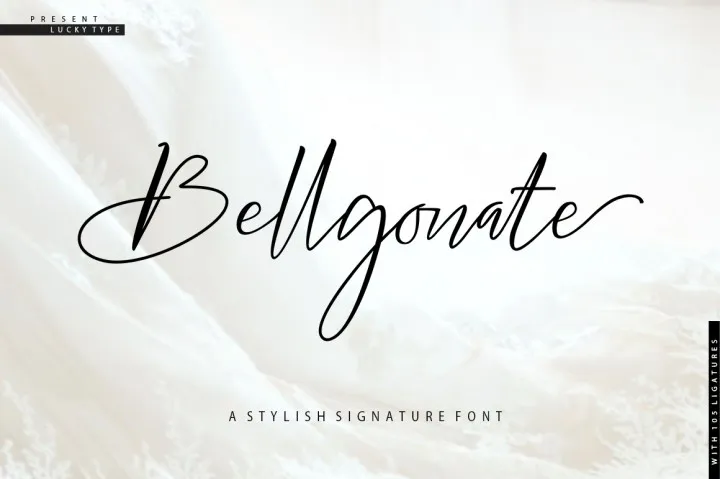
Bellgonate Signature Font – Download Grátis
A Bellgonate Signature Font é uma elegante fonte de script criada para dar vida a seu projeto com um estilo sofisticado e moderno. Seu designer privilegiado, 24Design, trabalhou arduamente para criar uma fonte que reflete o melhor da escrita manuscrita, oferecendo caracteres completos, incluindo letras maiúsculas normais e substitutas, para garantir um resultado impecável. Essa fonte é mais do que apenas bonita; ela possui uma natureza delicada e sofisticada, com traços finos e um estilo itálico. Seja em design gráfico, marca ou qualquer projeto que você esteja desenvolvendo, a Bellgonate Signature Font trará elegância e perfeição ao seu trabalho. Sua versão de swirls moderna garante uma apresentação sofisticada, suave e ideal para criações que exibem um ar único e diferenciado. Estar com essa fonte em sua coleção é como ganhar acesso a um conjunto completo de ferramentas de design gráfico. Ela é perfeita tanto para os profissionais quanto para aqueles iniciantes que querem incluir detalhes sofisticados em seus trabalhos, oferecendo uma maneira elegante de destacar seu trabalho e transmitir um forte impacto visual com cada letra escrita.